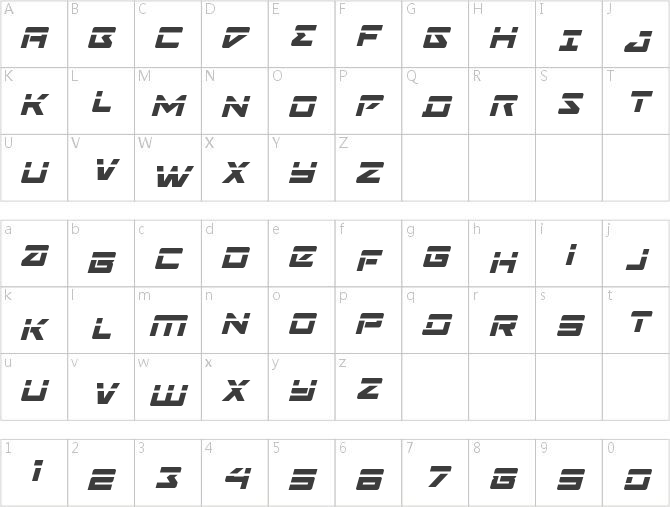
Navy Cadet Laser Italic
Navy Cadet Laser Italic介紹
Navy Cadet Laser Italic字體字庫是一款讓人賞心悅目、百看不厭的英文字體,適合各類廣告和產品包裝設計應用,字體大小0.03MB,格式為ttf字體,上傳用戶是素年錦時,作者/版權方為未知